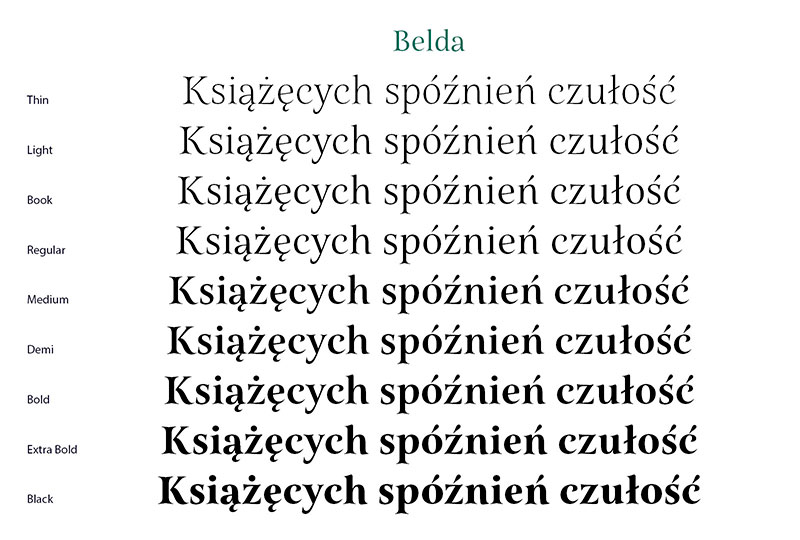
Font Belda
Do naszego studia trafił elegancki, szeryfowy font Belda, zaprojektowany przez Jeremiego Dooleya. Ma 9 odmian grubości, italiki, wersje skondensowane i rozszerzone.